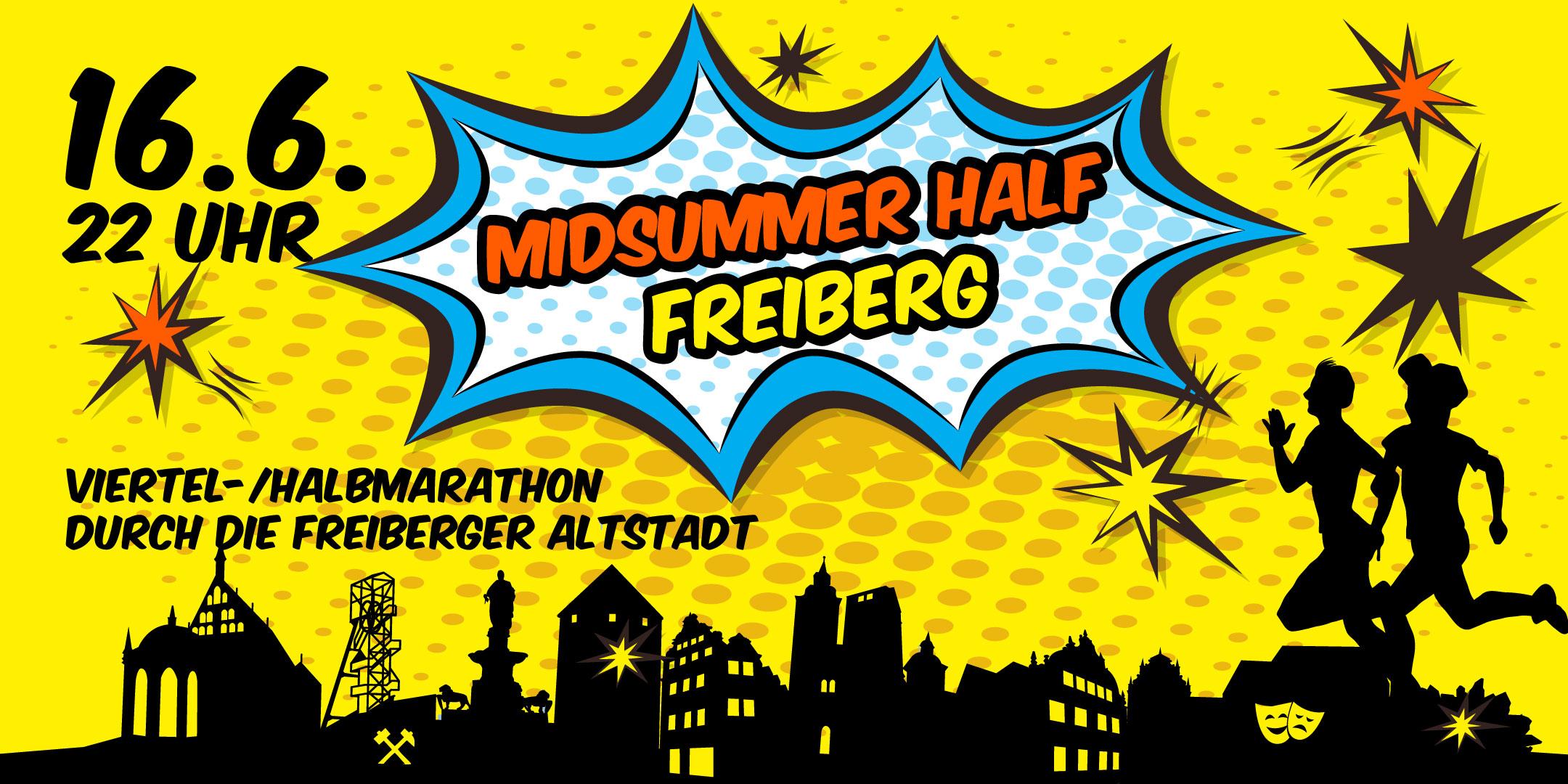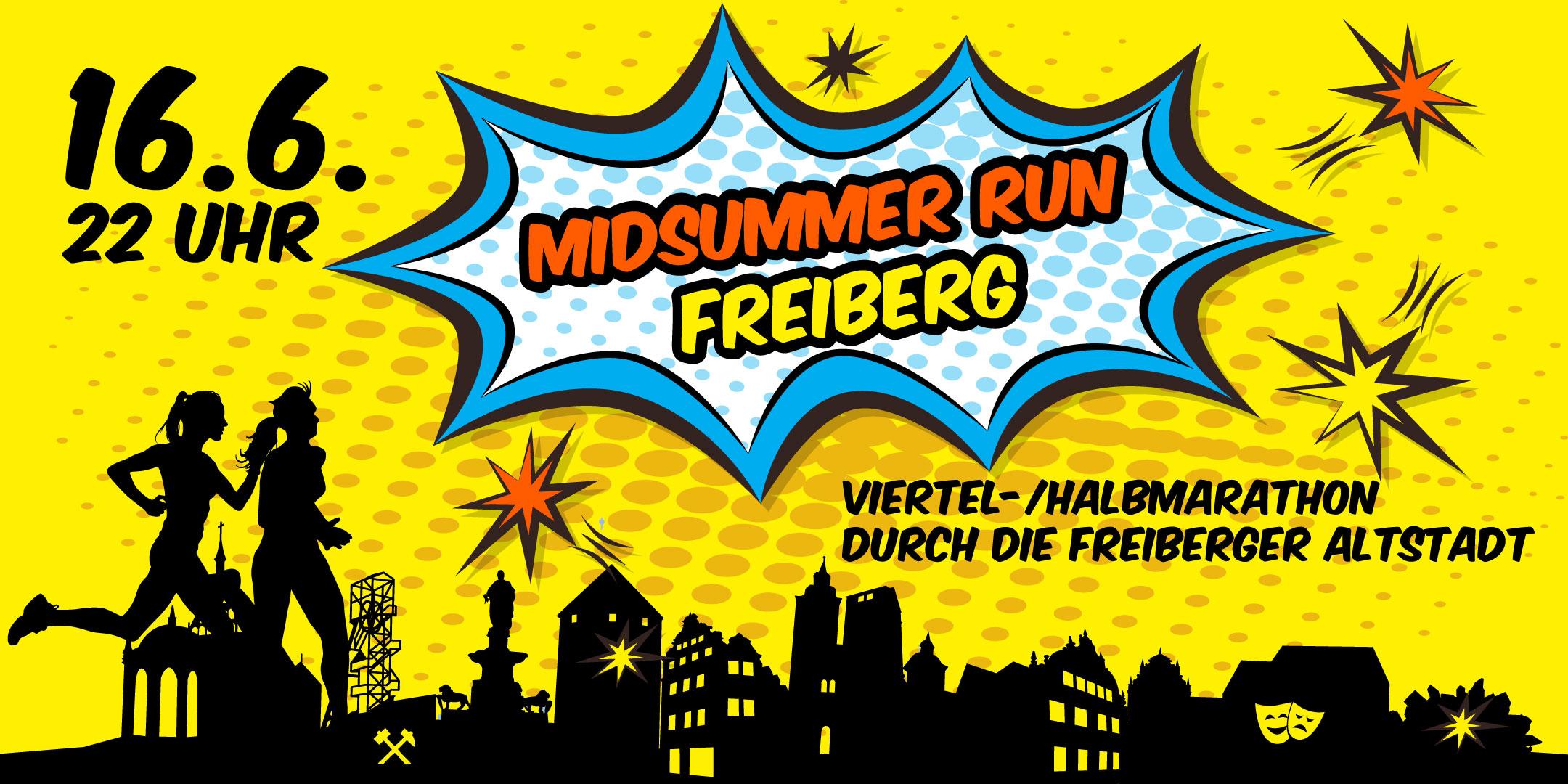
Schrift Midsummer Half
Geht mir auch so. vielleicht so:
MIDSUMMER MARATHON
21 km / 10,5 km
oder
MIDSUMMER MARATHON
21 oder 10,5 km
Warum ist 16.06. falsch?
Oder meint „falsch“ hier „unpassend für diesen Einsatzzweck“?
Man spricht ja »Sechzehnter Sechster« und nicht »Sechzehnter Nullsechster«. Das Gehirn liest aber die Null und muss sie dann erst »herausrechnen«. Das passiert dann zwar unbewusst und wohl im Millisekundenbereich, aber warum sollte man dem Leser das antun?
Trotzdem würde ich hier nicht kategorisch von »falsch« sprechen. :-?
Daher meine Frage. Vielleicht liegt es halt an meiner Leseerfahrung, dass ich eine Ziffer, die mit einer Null an das vorhergehende „Komma“ gekoppelt ist, eher als dazugehörig lese als ohne. „16. 6.“ lese ich eher als zwei zusammenhanglose Zahlen. „16.06.“ gehört für mich zusammen und scheint so eher ein Datum zu sein.
Ist für „16. Juni“ wirklich nicht genug Platz? :aschehaupt:
Ich befürchte, dass viele Betrachter gar nicht auf Anhieb schnallen werden, dass es da ums Laufen geht. Auf den ersten Blick sehe ich, dass da ein Event beworben wird …
• bei dem es ordentlich knallt (Feuerwerk?),
• das nachts stattfindet,
• zu dem alle hin (rennen) wollen/sollen.
Aber worum geht es? Vielleicht um Theater? :-? Bei Midsummer denke ich erst mal an Shakespeare, besonders in Verbindung mit dem Theatersymbol und der Tatsache, dass am 16.6. noch Frühling ist. Ob viele potentiell Laufbegeisterte das klitzekleine Halbmarathon finden, bevor sie weiter klicken?
Interessant diese Sicht von außen und deshalb ja auch die Frage in die Runde.  Die Idee haben wir übernommen und im Original heißt der Lauf Midnight Half - http://kummerani.de/2015/03/13/grosser-sport-der-tiderunners-midnight-half
Bei der Terminfindung hat dann der 16.06. optimal gepasst, und das liegt sehr, sehr nah am Mittsommerabend (23.06.2017). Deshalb dann von einem Sponsor (die Brauerei) die Idee MIDSUMMER ... Wir fanden und finden das originell, passend und verständlich. Klar könnten wir auch "Mittsommerabend Halbmarathon" nehmen aber ist das wirklich besser?
Der Banner steht ja so nie für sich allein und darunter immer der Text mit der Beschreibung. Der Hinweis mit den Masken und Shakespeare ist aber gut und richtig und deshalb fliegen die auch wieder raus oder ich verkleinere die.
Auch wenn eine DIN soetwas ›vorsieht‹ wird es dadurch nicht typographisch richtig. Die dort aufgelisteten Möglichkeiten sind ja eher nach dem Motto »jetzt probieren wir mal alles aus« zusammengestellt, reine Theorie, kaum praxistauglich. Typisch Technokratie eben.
Ein Datum schreibt man 16. 6. oder 16. Juni – alles andere ist Quark (es sei denn es gibt z.B. sortiertechnische Gründe, das Jahr voranzustellen, aber das sind Sonderfälle).
Wie Kathrin schon schrieb: die vorgekoppelte Null ist im Tabellensatz richtig, weil sie dort eine Funktion hat. Bei allen anderen Satzanwendungen ist sie falsch*, weil sie da keine Funktion, keinen Sinn und keinen Nutzen hat. Macht man es dennoch, bewegt man sich auf dem Level »Deppen-Apostroph«.
D. h. sie ist auch insbesondere beim Satz eines Datums falsch. Eine 6 ist eine 6 und keine 06.
* eindeutig typographisch falsch.
Bitte /- in -/ ändern ;-)
Kann die Veranstaltung nicht »Run« o.ä. heißen? Unter "Half" denk ich eher an die Halfpipe …
Die Bewegungsrichtung würde ich der Leserichtung anpassen, also die Mantschgerl nach rechts laufen lassen.
Und vielleicht ein paar der Blitze weglassen – sieht mir zu sehr nach Silvester aus.
Kann Sie :-) Noch ist es nicht zu spät für Änderungen jeder Art. Danke für den Tipp. Habe gerade mal in die Orga-Runde gefragt und die finden Midsummer Run auch besser. Damit legen wir uns auch nicht auf die Streckenlänge fest und es ist ja nicht nur der Halbe :-)
Deswegen würde ich auch kein Leerzeichen dazwischen machen, sondern nur einen Mini-Abstand.
Alle Sterne im Bereich außerhalb der Silhouette[?]
Genau :nicken:
Sollte man dann nicht auch den fehlenden Kopplungsstrich bei »Midsummer Run« bemängeln? Schließlich findet die Veranstaltung in Deutschland statt. ;-)
Warum dann nicht gleich Mittsommer-Lauf  (oder halt Mittsommerlauf)? Ich würde es so machen oder eben Englisch – dann aber komplett – bleiben.
Sonst spielen deutschsprachige Freunde des rotationsellipsoiden Ballspiels dann demnächst vielleicht American-Football! :neenee: